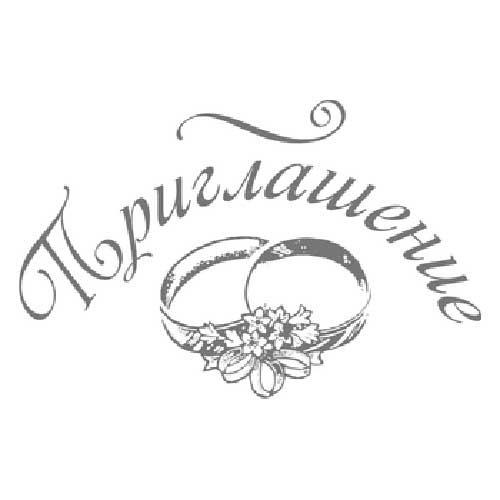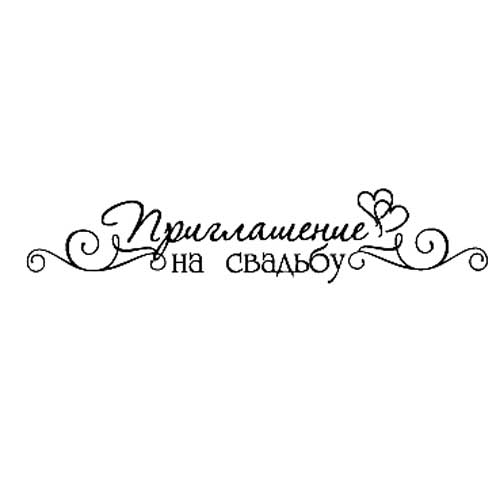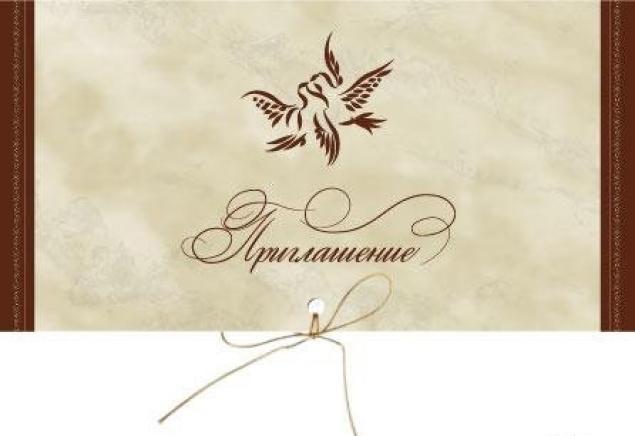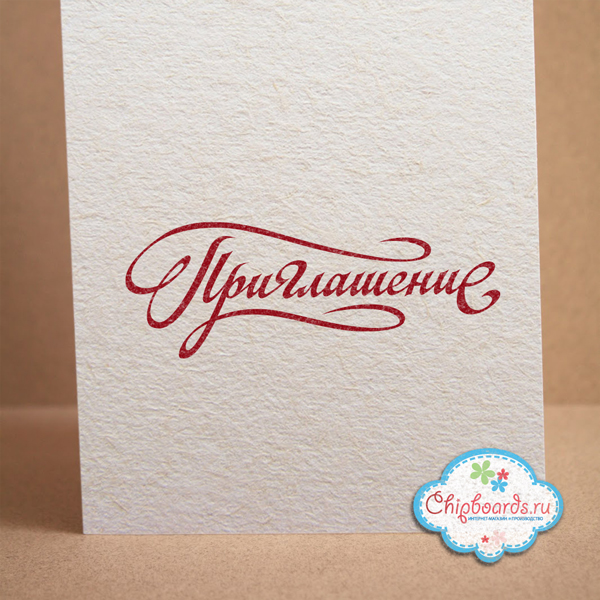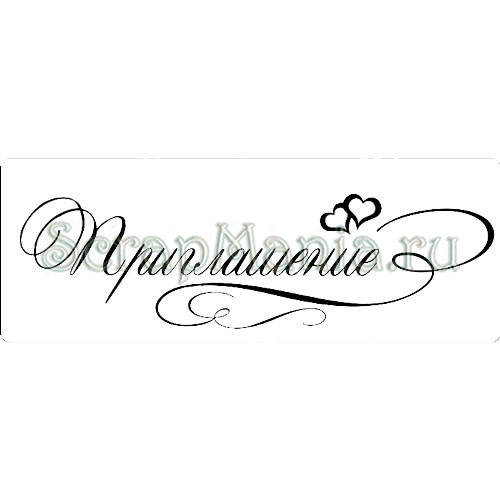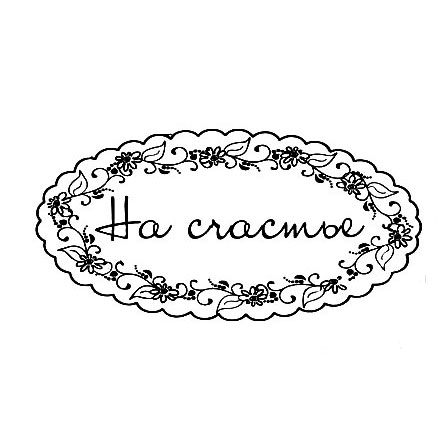
С днём рождения надпись красивым шрифтом
В случае необходимости использовать красивую надпись «C Новым годом» или «C Днём Рождения» рекомендуем обратиться к онлайн сервису, при помощи которого можно написать любой текст красивым шрифтом, как на русском, так на английском языке.
Выбор шрифтов генератора очень богат и разбит на категории: Киррилица, Печатный, Плавные Каллиграфические, Сказочный, Декоративный, Контурный, Техно, Gothic и другие.
Существует масса причин по которым может понадобиться надпись: «С Днем Рождения!». Например, вы сами изготавливаете открытку на день рождения, и осталось лишь добавить буквы. Ниже, вы можете выбрать и скачать понравившийся вам вариант надписи, которая сохранена в формате PNG с прозрачным фоном.
Надписи С Днем Рождения разными цветами
Следующие надписи лучше всего подойдут для темного фона. Для скачивания доступна голубая, розовая, салатовая и оранжевая надписи. Буквы выполнены в высоком разрешении и помещены на прозрачном фоне.
Надписи С Днем Рождения разными стилями и шрифтами
Надписи имеют ширину 2000 пикселей. Благодаря формату PNG, в котором сохранена каждая надпись: «С Днем Рождения!», фон изображения — прозрачный.
Надписи «С Днем Рождения!» в две строчки
Данная надпись выполнена красным цветом с тенью и имитацией объемных букв.
Приглашения на свадьбу своими руками техника скрапбукинг. Креативные пригласительные на свадьбу своими руками
Приглашения – это серьезная заявка на победу в свадебном марафоне, который начинается задолго до торжества. Завершиться он должен ярким и трогательным праздником, который надолго запомнится всем присутствующим.
Можно сказать, что свадебные приглашения – визитная карточка будущего супружеского союза .
Многие молодожены здесь сталкиваются с дилеммой. С одной стороны, стандартные открытки кажутся им банальными и старомодными ( на фото красивых открыток). А с другой – услуги профессиональных дизайнеров требуют дополнительных вложений, в то время как бюджет и без того рассчитан до рубля.
Chantelli Antiqua отлично подходит для текста в приглашениях или заголовков на этикетках и тегах.Он отлично работает в паре с простым шрифтом sans.
АФИНА
Этот короткий и прочный элегантный шрифт Athene был разработан Мэттом Эллисом. Афина отлично подходит для заголовков и заголовков в журналах или для стильных приглашений. Этот специальный шрифт также отлично подходит для логотипов и тегов свадебных сидений. Это универсальный шрифт, который хорошо сочетается с модными брендами, а также с редакционными концепциями.
ВОЛЛКОРН